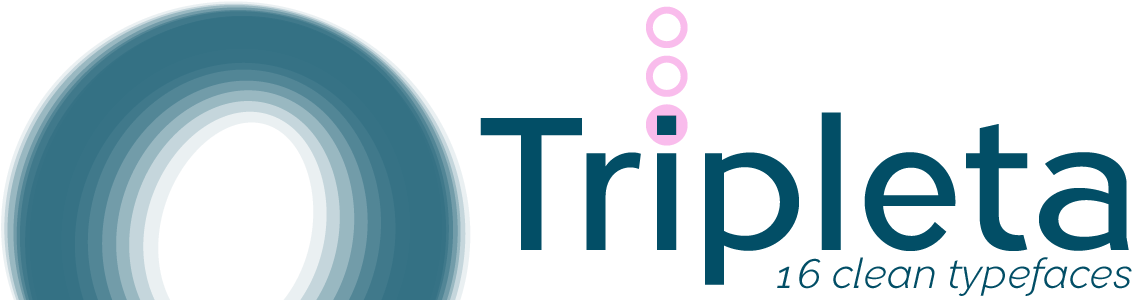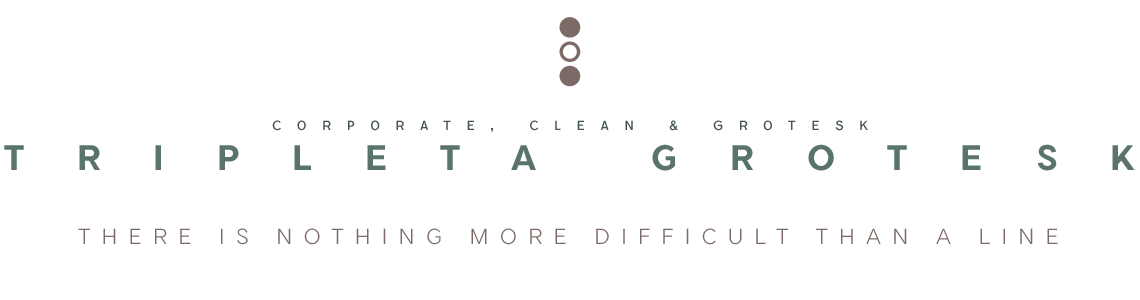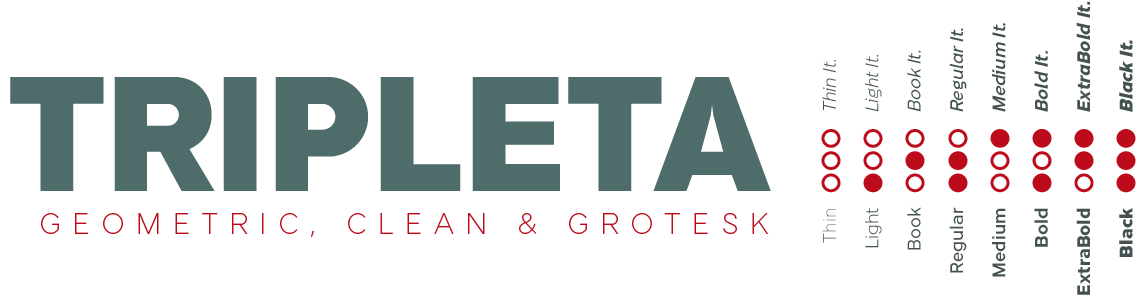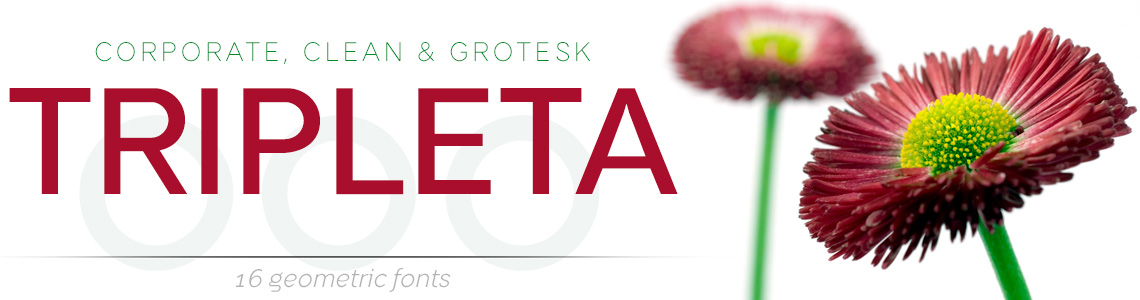
En el desarrollo de estas fuentes he definido cuidadosamente la anchura de cada letra y la anchura de las astas verticales y horizontales así como las métricas y el Kerning para conseguir un juego de letras equilibrado de la máxima legibilidad en cualquier tamaño y para multitud de usos en diseño gráfico, editorial, señalización, etc. cubriendo todas las necesidades de escritura que requiere cualquier proyecto corporativo o publicitario.
Grotesk family fonts
Estilo: Sans Serif, Geométrica, Corporativa, Neo Grotesca
Proporción: Thin, Light, Book, Regular, Medium, Bold, ExtraBold & Black + Italics